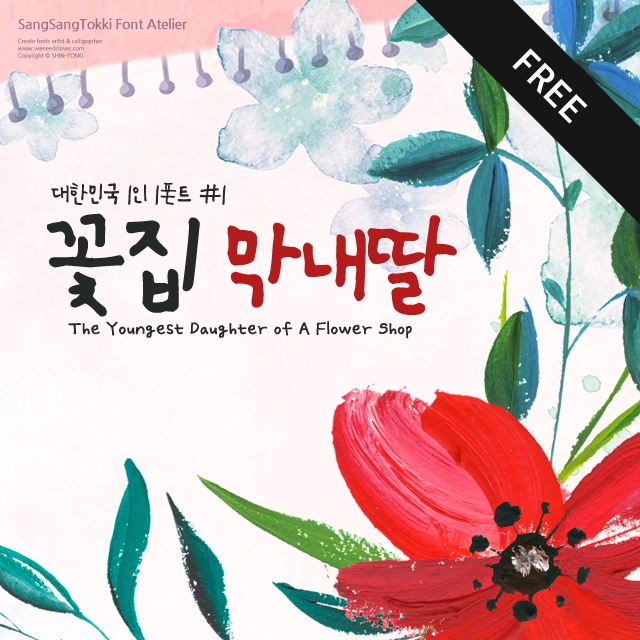
꽃집 막내딸
꽃집 막내딸로 태어나 꽃과 함께 자란 지혜가 나누는 감성 손글씨 폰트, 꽃집 막내딸
한글 2,479자 / 영문 52자 / 약물 54자
꽃집막내딸 Regular 1종
꽃집 막내딸로 태어나 꽃과 함께 자란 지혜가 나누는 감성 손글씨 폰트 <꽃집 막내딸>은 상상토끼 용이 작가의 대한민국 1인1폰트 첫번째 주인공인 강지혜씨의 손글씨를 기초로 해서 만들어진 폰트입니다. 소중한 글씨로 멋진 폰트를 만들게 허락해준 꽃집 막내딸에게 감사의 마음을 전합니다. |